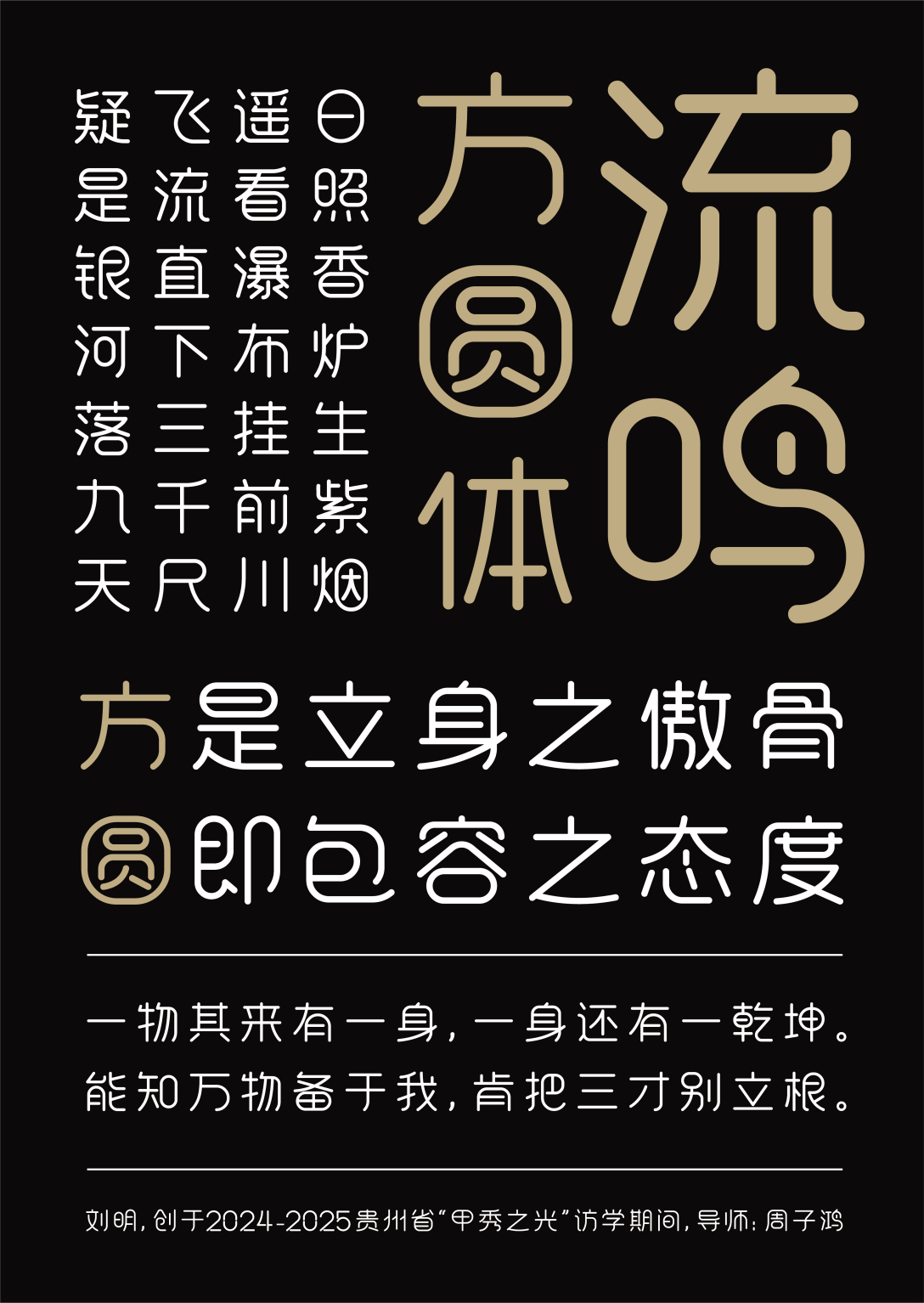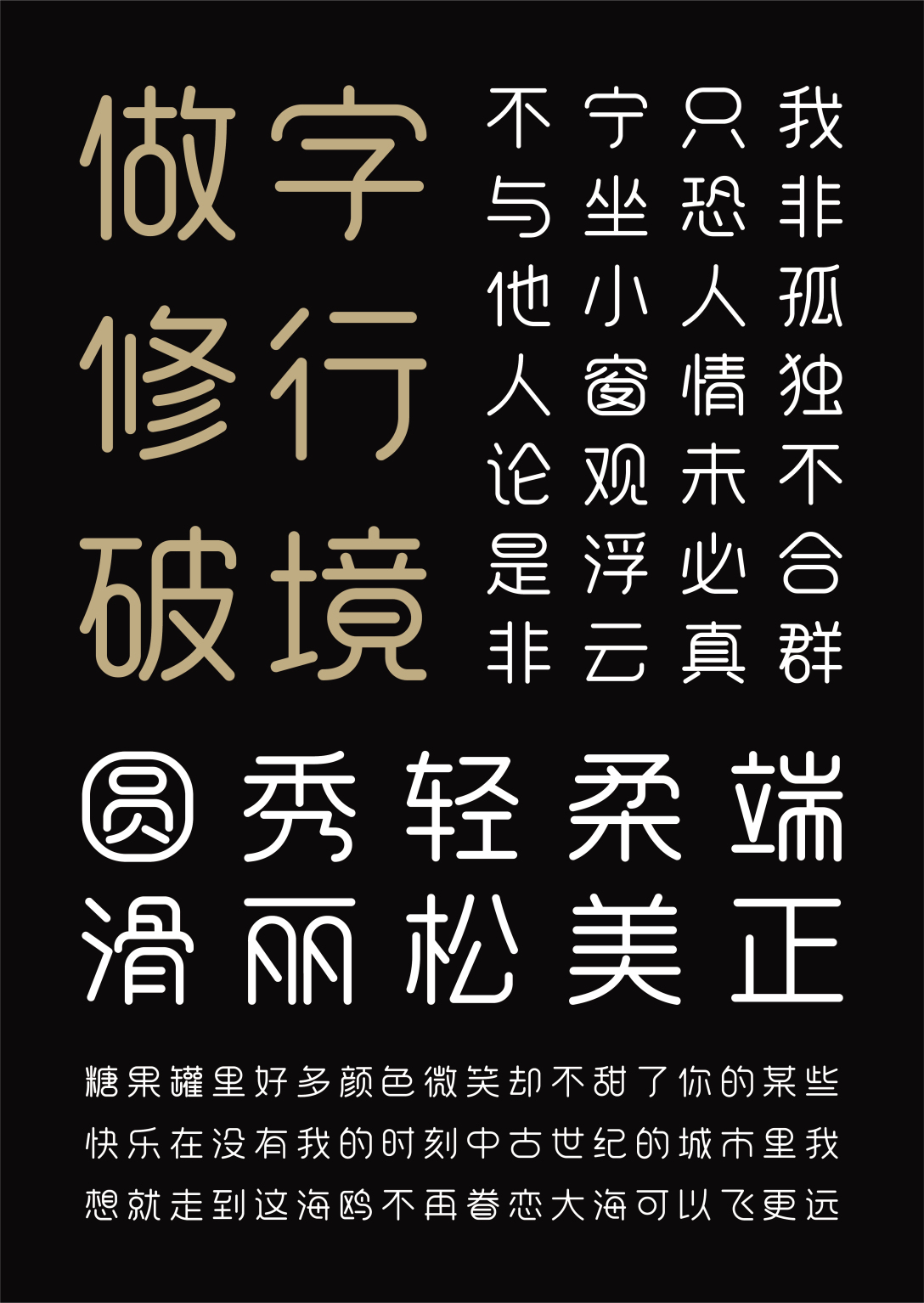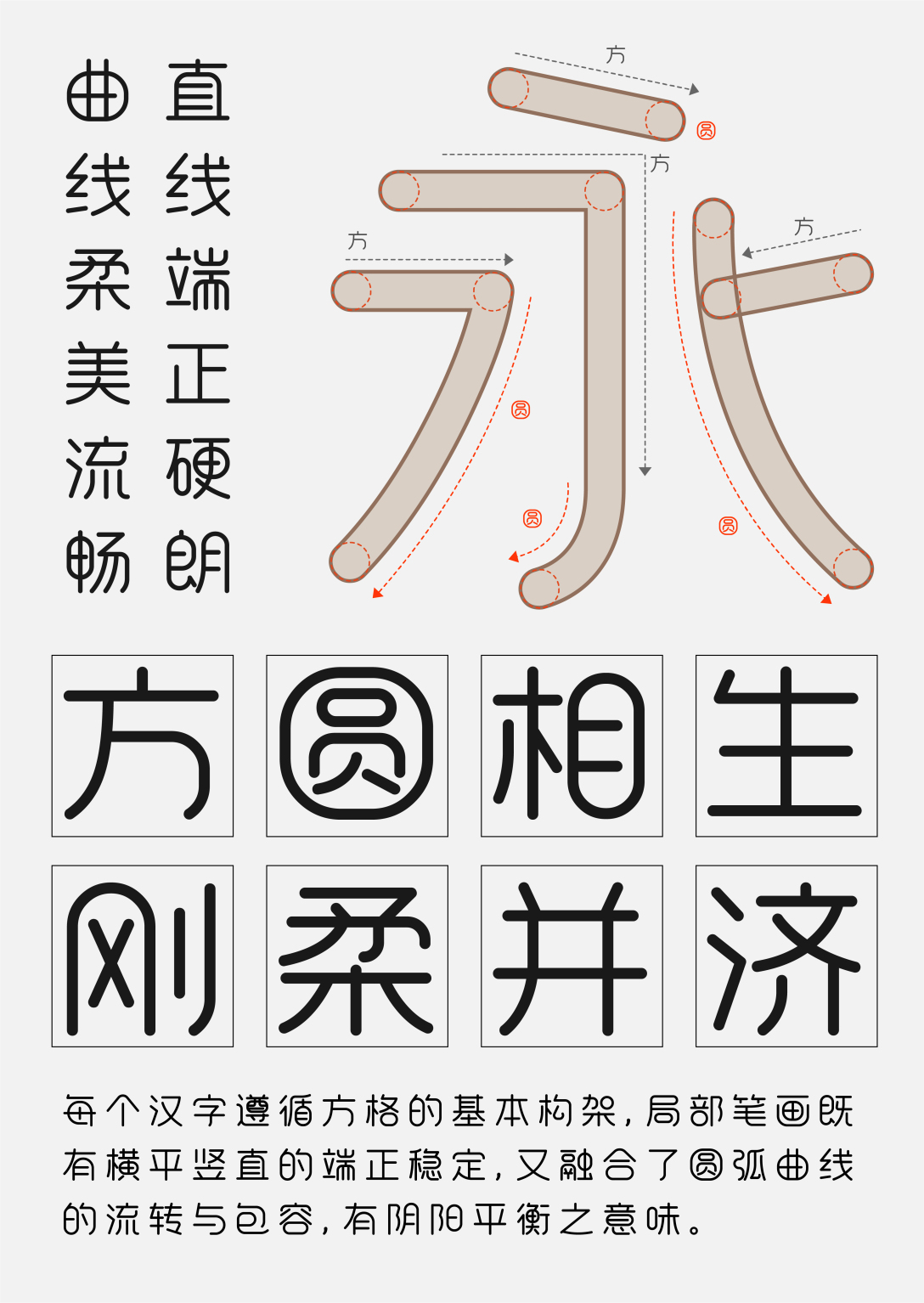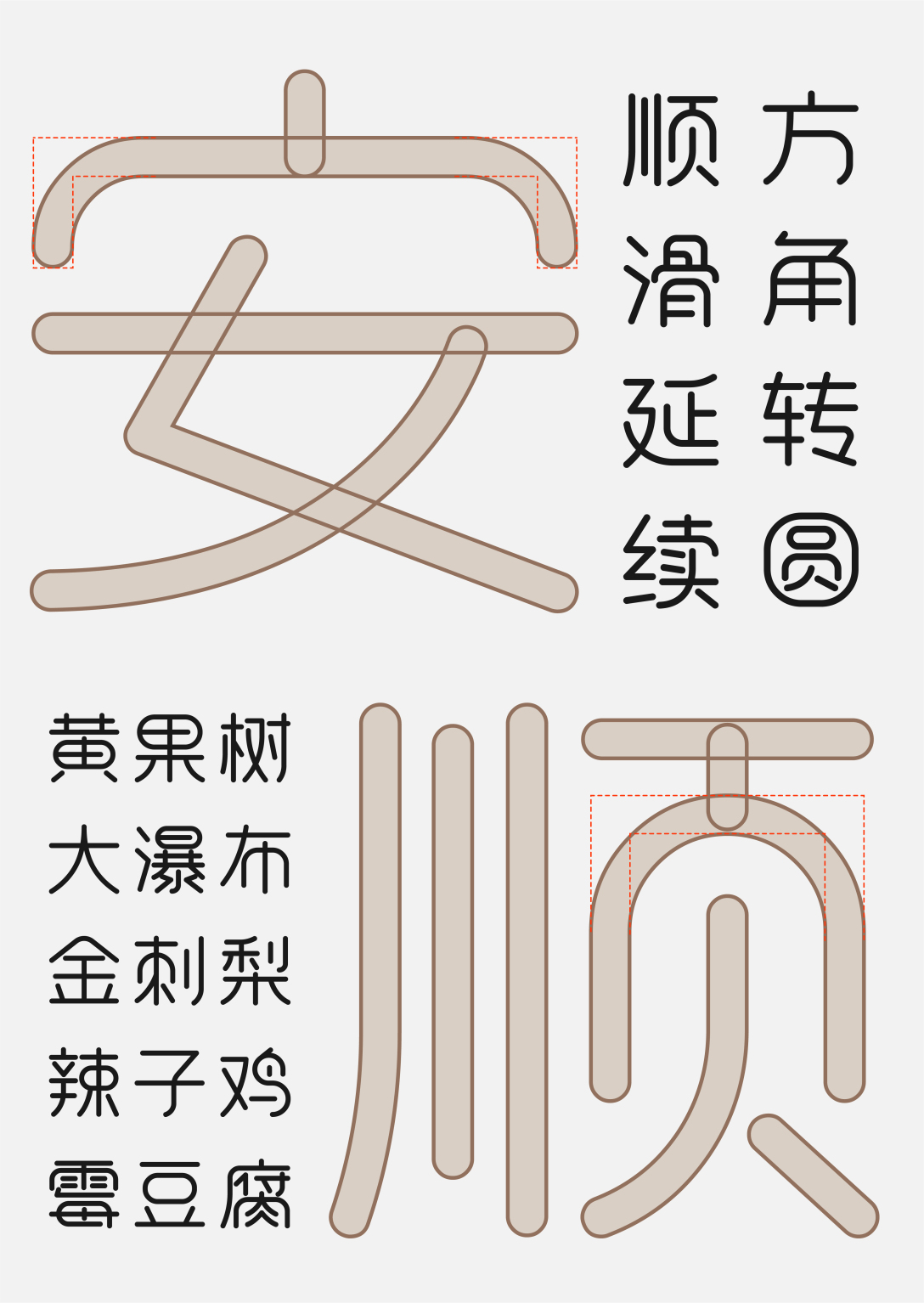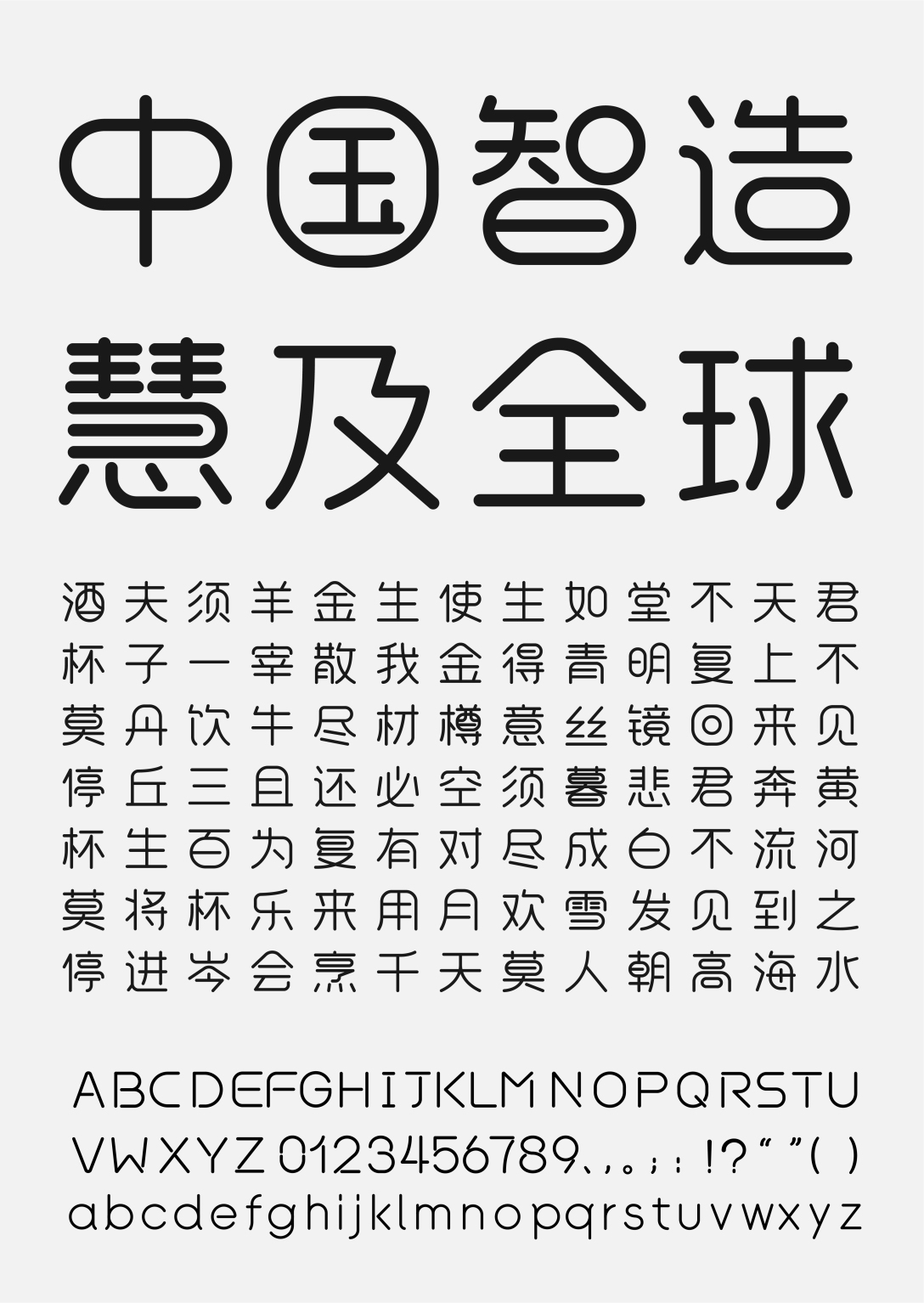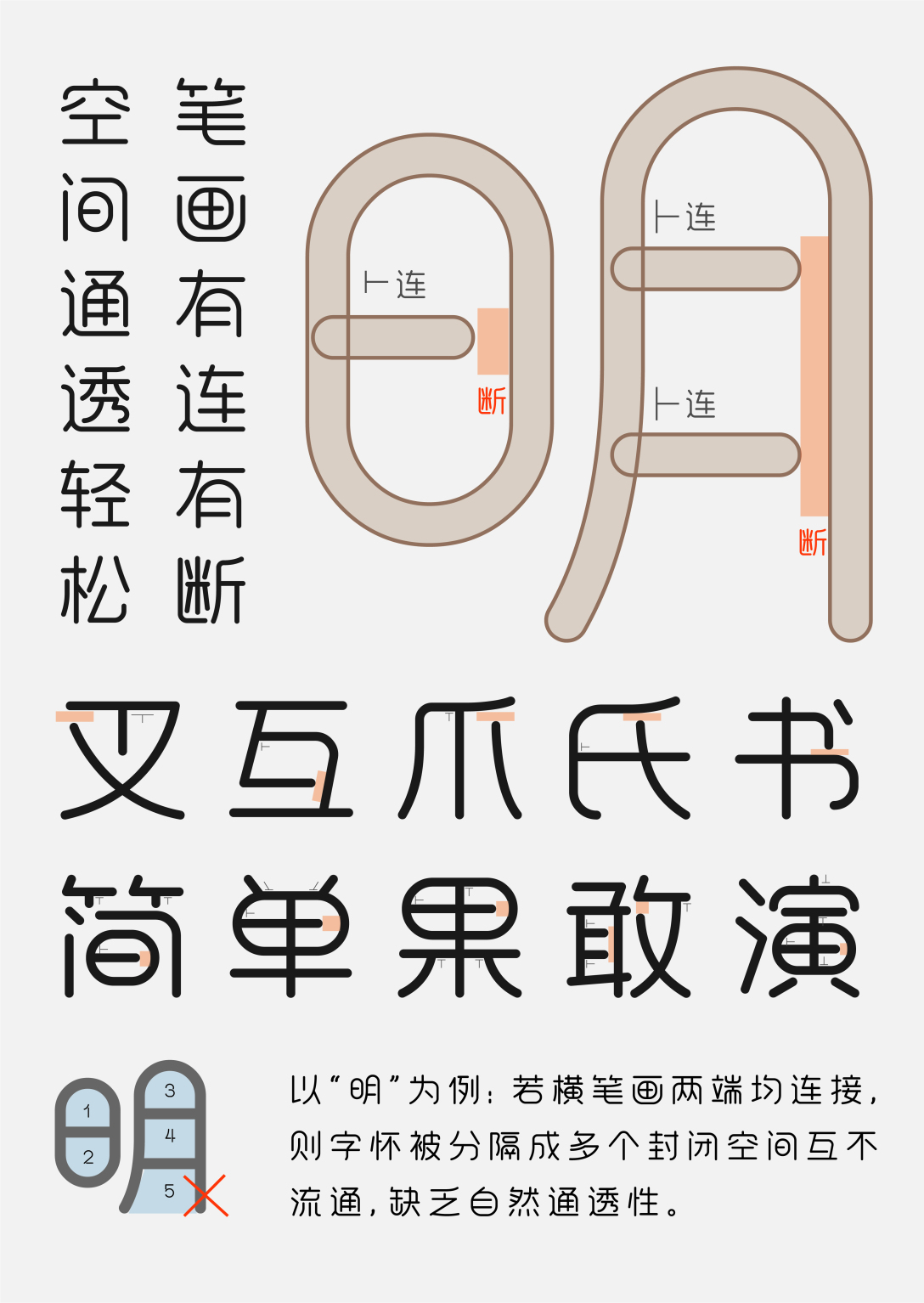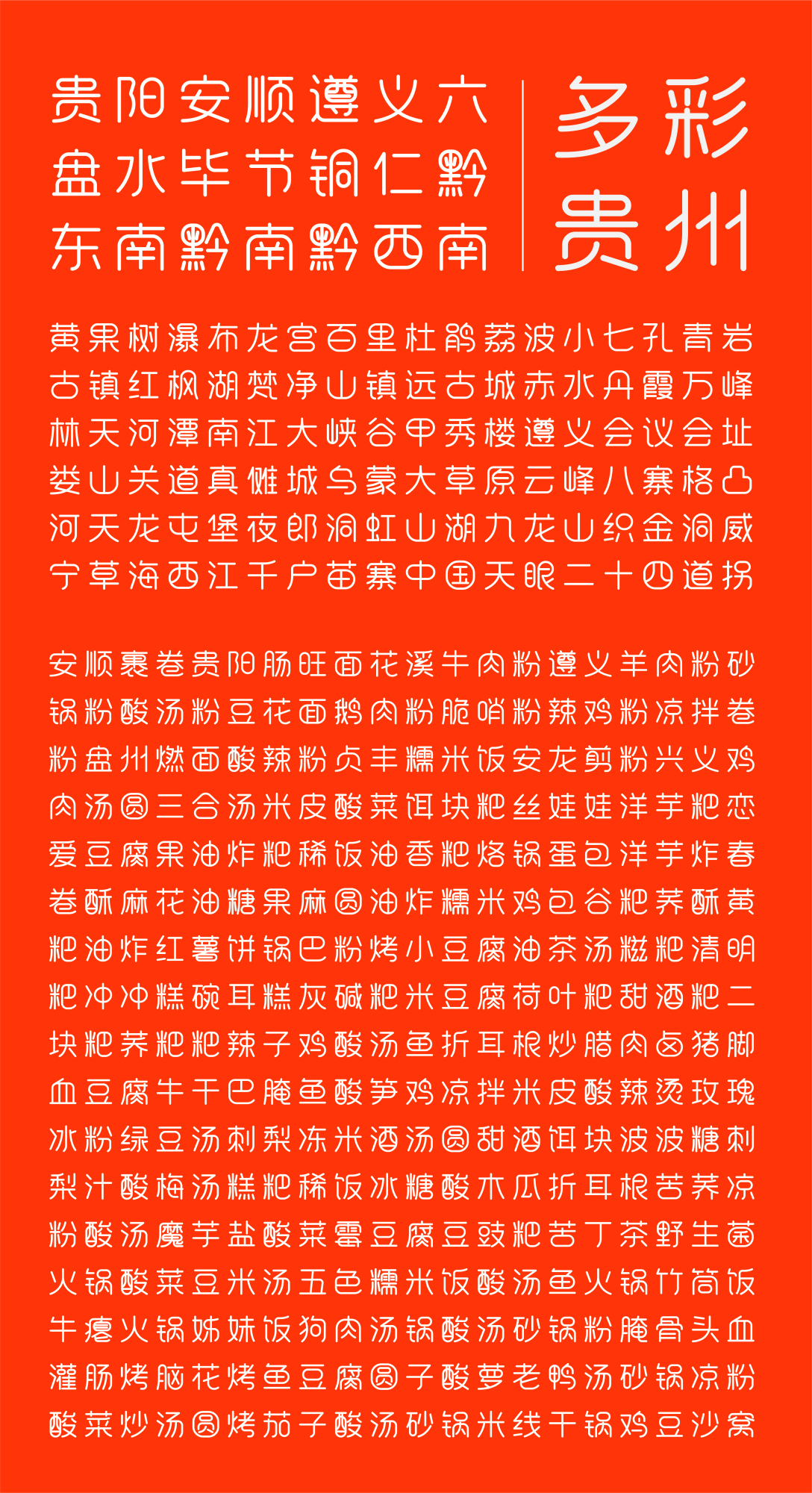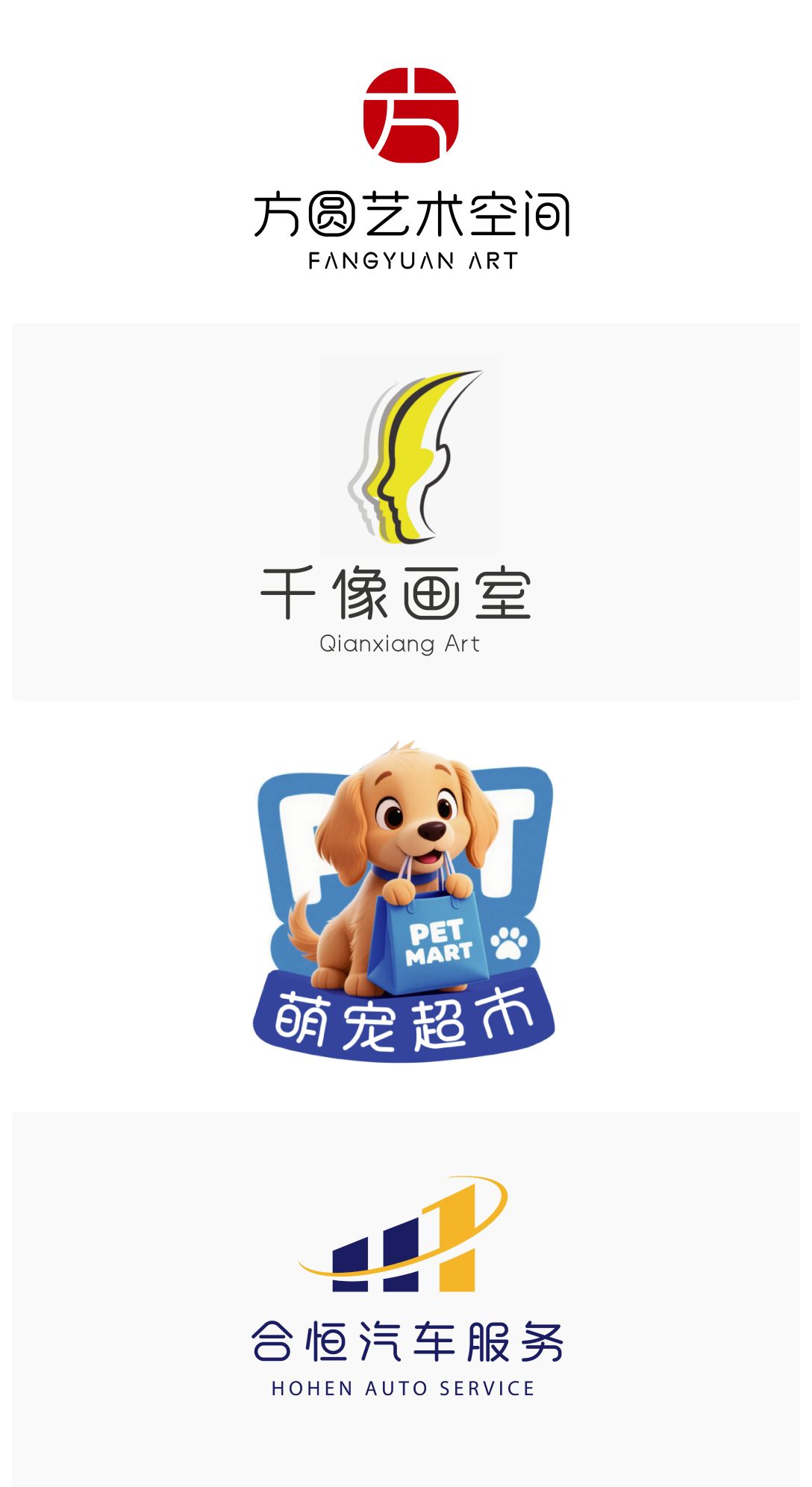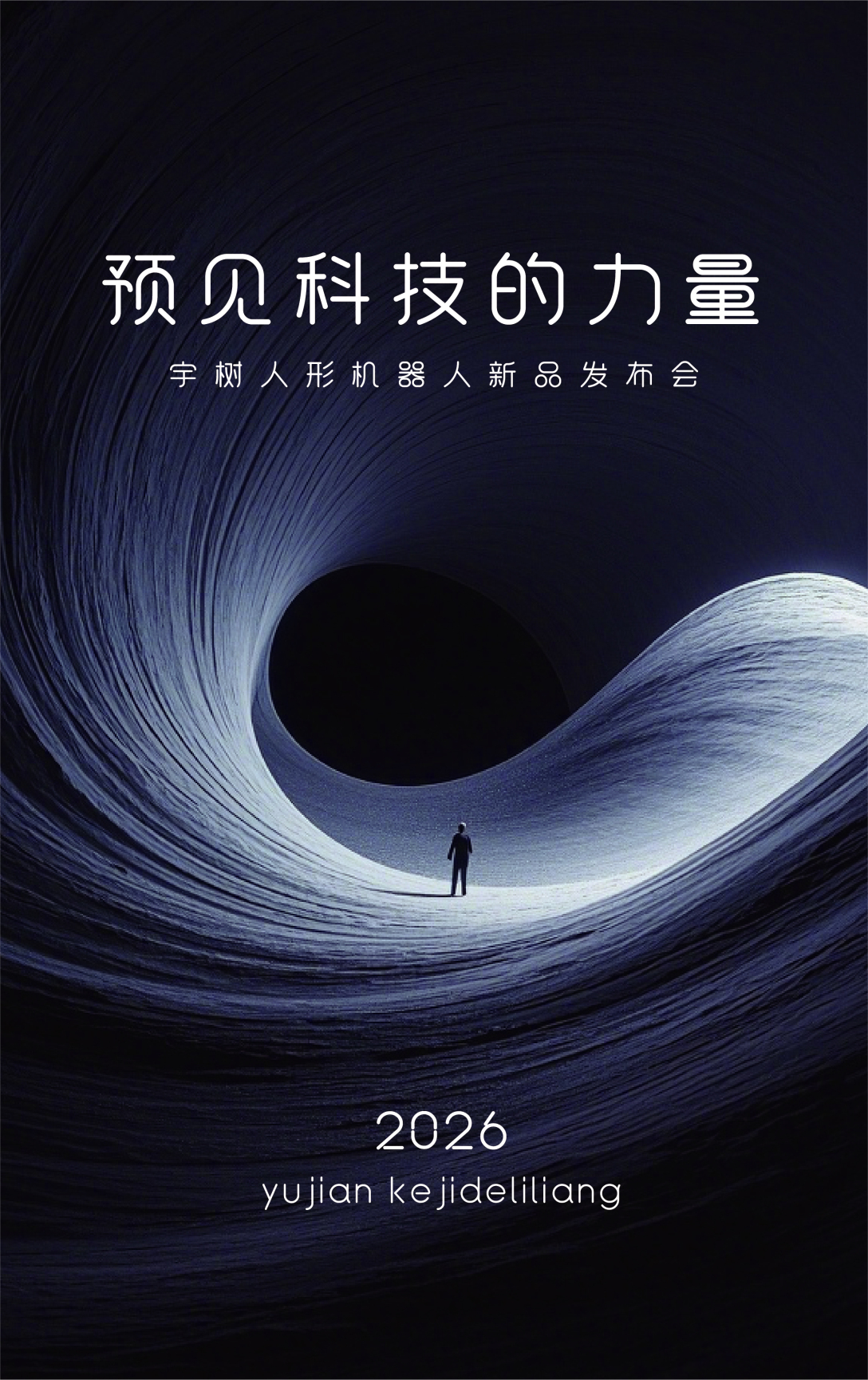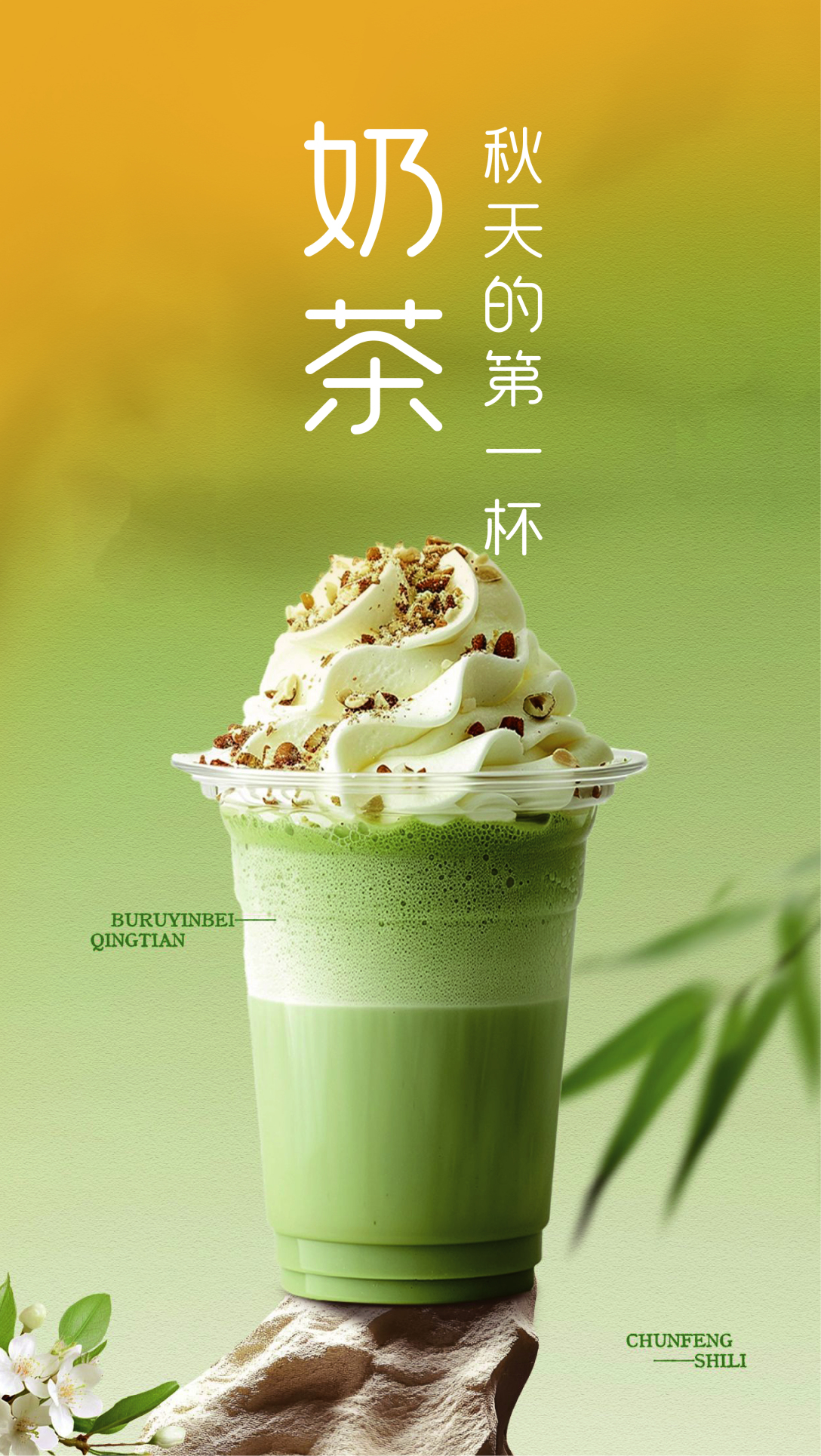
流鸣方圆体字体设计解读
从设计理念的哲学内核、字形笔画的创新表达、风格适配的多元场景及地域文化的隐性融合四个维度,剖析其如何以“方圆相生”为核心,平衡刚柔特质,打造出兼具美学深度与实用价值的创意字库字体,为现代设计提供独特的视觉语言。
流鸣方圆体的设计理念深植于“方圆相生”的东方哲学,将“方”的端正傲骨与“圆”的包容态度融入字体基因。正如页面中“方是立身之傲骨,圆即包容之态度”的表述,这款字体打破了传统字体非方即圆的单一形态,以“阴阳平衡”为设计准则——每个汉字均遵循方格基本构架,保证“方”所代表的稳定与规整,如同立身行事的原则底线;同时在局部笔画融入圆弧曲线,传递“圆”所象征的流转与包容,恰似待人接物的灵活态度。这种设计不仅是视觉层面的创新,更将“破境修行”的创作思考注入其中,让字体成为“一物一乾坤”的哲学载体,在横平竖直与圆弧流转间,展现东方文化的辩证智慧。
在字形与笔画设计上,流鸣方圆体通过“刚柔并济、连断结合”的手法,构建出兼具识别性与艺术感的视觉特质。笔画处理上,直线部分端正硬朗,如横平竖直的架构支撑起字体的“骨感”,传递出力量感与稳定性;曲线部分柔美流畅,圆弧过渡自然顺滑,为字体注入“肉感”与灵动性,避免机械的规整。同时,字体借鉴手写连笔特征,对部分偏旁或笔画组合进行简化连笔设计——例如将多个独立笔画融合为连贯线条,既保留文字的基本识别性,又提升了书写的流畅感与非凡气质。空间布局上,设计团队注重“通透轻松”,以“明”字为例,通过控制横笔画的连接范围,避免字怀形成封闭空间,让字符内部视觉流通,既缓解了阅读时的压抑感,又增强了字体的呼吸感与自然度。
从风格适配性来看,流鸣方圆体凭借“刚柔平衡”的特质,展现出极强的场景包容性,可跨越文化、商业、生活等多个领域。在文化场景中,其方圆融合的气质适配古典诗文排版(如页面中“飞流直下三千尺”的诗句)、地域文化宣传(如贵州“多彩黔”主题设计),既能传递传统文化的雅致,又不失现代设计的简洁;在商业场景中,可用于品牌LOGO(如“合恒汽车服务”“宇树人形机器人”)、产品包装(如“高山小米”“刺梨原液”“云南鲜花饼”),直线的硬朗感适配科技、汽车等强调专业的领域,曲线的柔和感则契合食品、文创等注重温度的品类;在生活场景中,也可用于自媒体文案、儿童读物、日常标识等,连断结合的笔画设计既保证易读性,又增添视觉趣味,满足不同用户的审美与实用需求。
值得关注的是,流鸣方圆体还隐性融入了贵州地域文化元素,成为地域特色与字体设计结合的典型范例。页面中大量提及贵州的地名(贵阳、安顺、遵义等)、自然景观(黄果树瀑布、梵净山等)、美食(肠旺面、羊肉粉等),推测字体在创作过程中,可能从贵州的自然与人文中汲取灵感——例如曲线的流畅感或许呼应贵州山水的蜿蜒灵动,直线的挺拔感可能暗合甲秀楼等建筑的端正格局;同时,字体在“多彩黔”“中国天眼”等地域IP的应用中,能精准传递贵州的多元文化气质,让字体不仅是通用的文字符号,更成为连接地域文化与外界认知的视觉桥梁。此外,完整的中西文字符集(含大小写字母、数字、标点)进一步拓宽了其应用边界,使其在中西文混排场景中仍能保持风格统一,适配全球化传播需求。